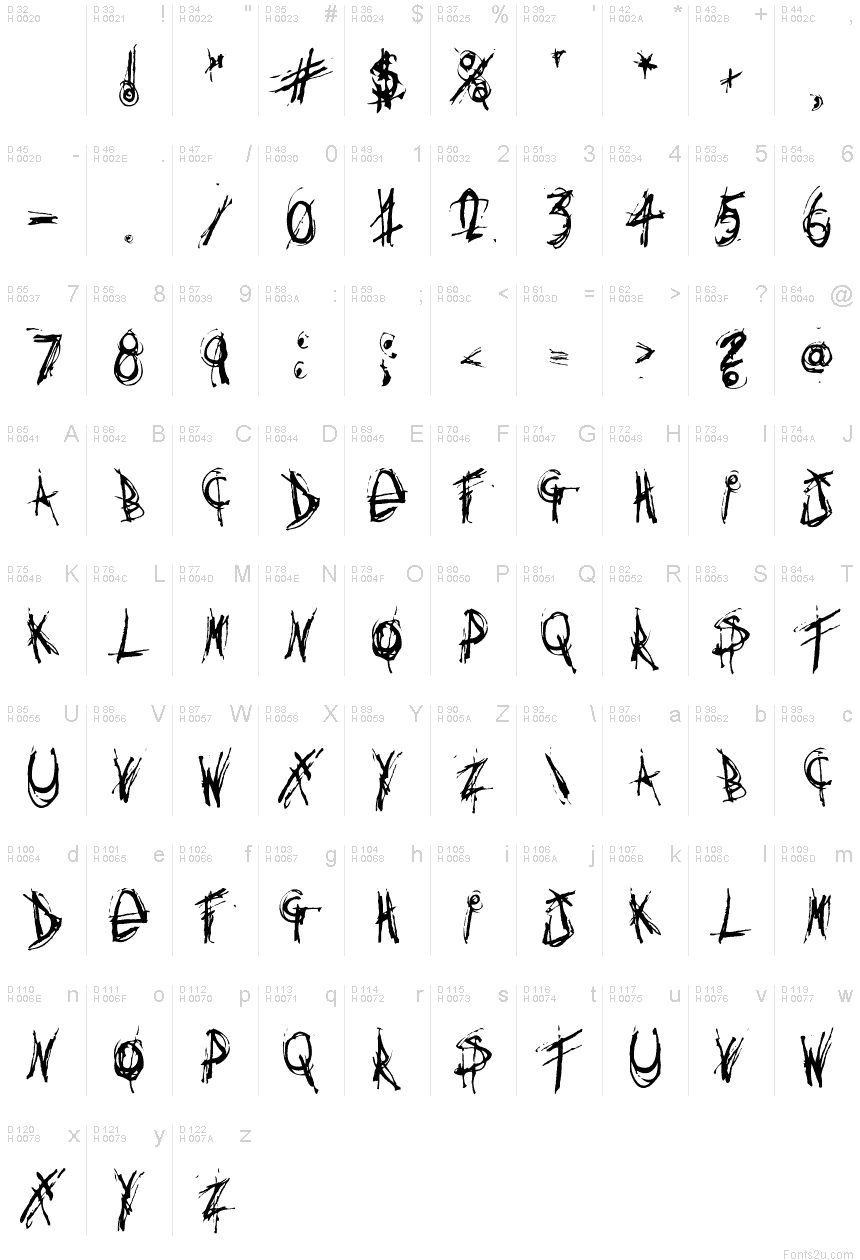
Anything You Want od Alex C je bezplatné písmo ve stylu trash script, které vypadá, jako by bylo vyškrábané do stránky inkoustovými, roztřepenými tahy. Písmena se kroutí, kapou a vystřelují ven s nervózním rytmem, který působí syrově a lehce vyšinutě – jako graffiti vyškrábané do kovových dveří. Nepravidelné rozestupy a potrhané tvary dodávají každému slovu frenetickou, ručně vytvořenou energii, kterou lze jen těžko napodobit u čistších skriptových písem.
S použitím Anything You Want váš text nešeptá – on křičí. Toto bezplatné písmo vynikne na hororových plakátech, obalech punkových nebo metalových alb, DIY letácích, grunge zinech, skate a streetwear značkách i odvážné grafice na sociálních sítích. Použijte ho ve velkém, aby stříkance a škrábance zůstaly čitelné, a pro hlavní text ho doplňte jednoduchým, zúženým bezpatkovým písmem, aby chaos zůstal soustředěný tam, kde na tom záleží.
copyright Alex C 2001. - "Anything you want" A grunge handwriting font, made from my graffiti caps writing.
Anything You Want